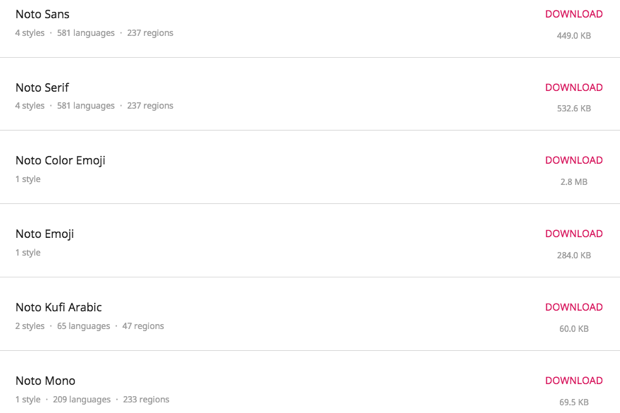
เบื่อฟ้อนต์เก่าๆกันแล้วหรือยัง? ถ้าเบื่อแล้วมาลองของใหม่กันดีกว่า ของใหม่ที่ว่าก็คือฟ้อนต์ Noto จาก Google ฟ้อนต์ ที่สามารถแสดงผลได้เกือบทุกภาษาทุกเผ่าพันธุ์บนโลกนี้ “Beautiful and free fonts for all languages” คือ Keyword หลักของฟ้อนต์ฟรีชุดนี้
ฟ้อนต์ชุดนี้ใช้เวลาสร้างถึง 5 ปีเลย กว่า 800 ภาษาที่ฟ้อนต์ฟรีชุดนี้มาสามารถแสดงผลได้ถือว่าไม่ธรรมดาจริงๆ ใครเบื่อฟ้อนต์ Tahoma แบบเดิมๆแล้วลองหันมาใช้ Noto กันดีกว่า ฟ้อนต์ชุดนี้น่าจะมีผลกับสื่อ Digital มากที่สุด เพราะฟ้อนต์ที่จะใช้เป็นตัว Content ในอนาคตบนสื่อออนไลน์นั้นควรจะมีลักษณะที่คล้ายกันและพร้อมแสดงผลได้กับทุกภาษาบนโลกใบนี้ ใครทำแอพพลิเคชั่นหรือทำเว็บไซต์อยากให้ลองศึกษาฟ้อนต์ฟรีตัวนี้ดูครับ